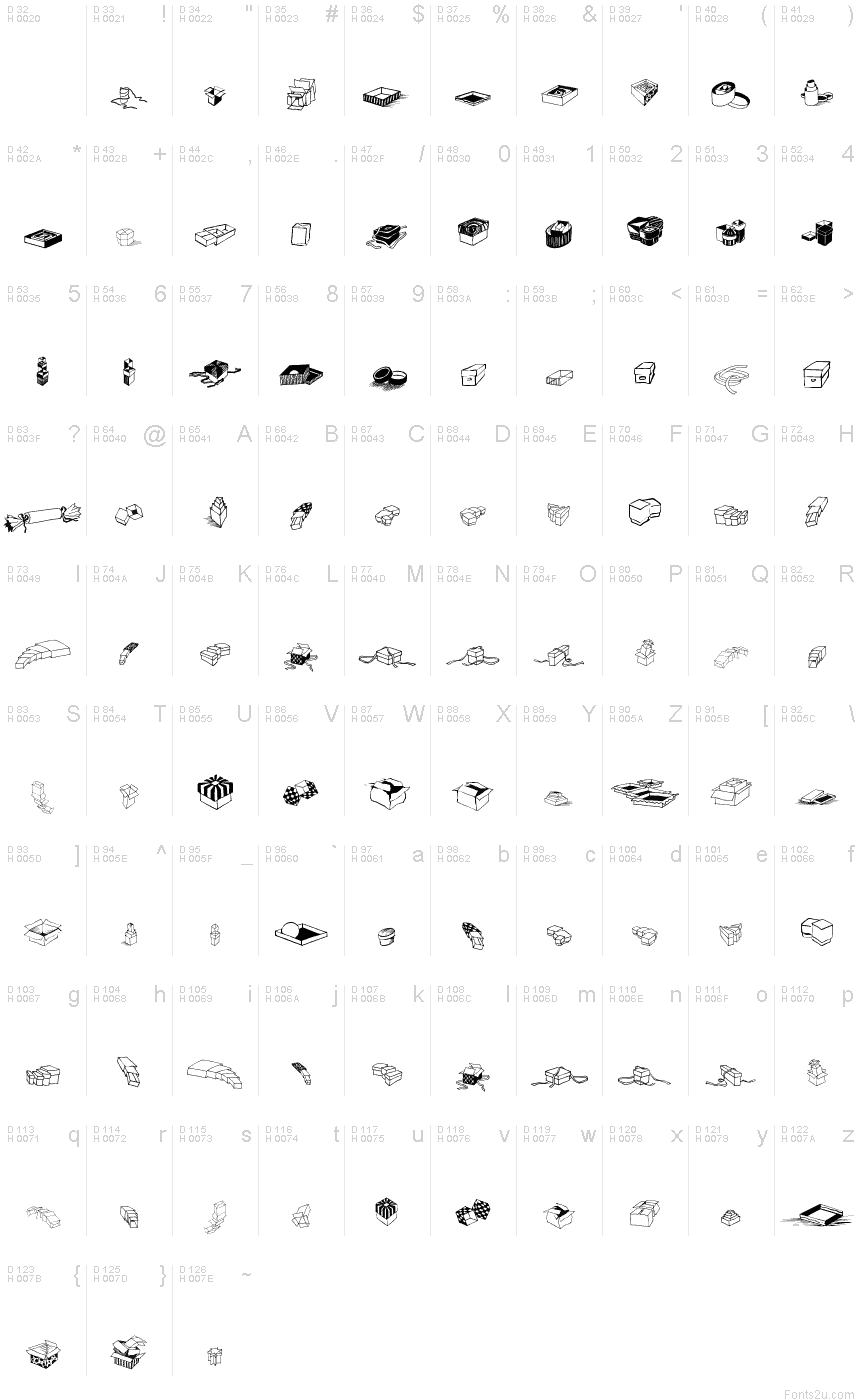
Zoeboxes od Zoe Keramea je bezplatný dingbat font z roku 1994 s ručně kresleným svátečním nádechem. Sada obsahuje zabalené dárky, otevřené krabice, stužky a lehce nepravidelné obrysy, které kresbám dodávají živý a autentický vzhled, namísto příliš dokonalých linek.
Skvěle se hodí na pozvánky na večírky, sváteční přání, stránky scrapbooků, maloobchodní obaly nebo hravé akcenty na letácích, kde tento bezplatný font s hotovými motivy dárků umožní rychle vyřešit vizuální stránku. Použijte jej na krátké nadpisy, ozdoby v rozích, grafiku na štítky nebo jednoduché slavnostní oddělovače – díky rozvlněným stužkám a tvarům krabic působí i drobné detaily živě a slavnostně.